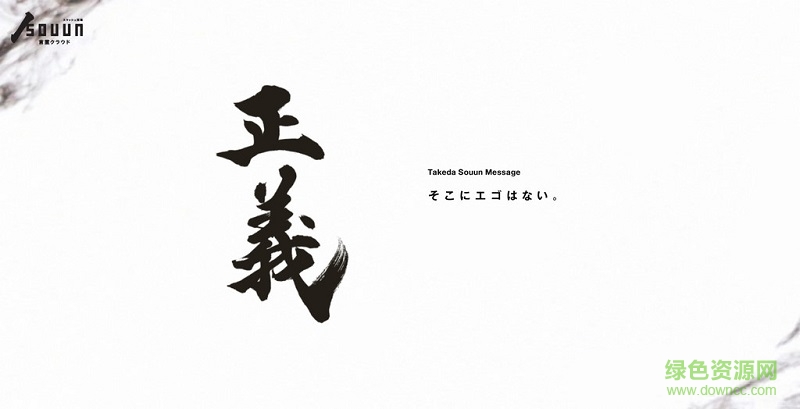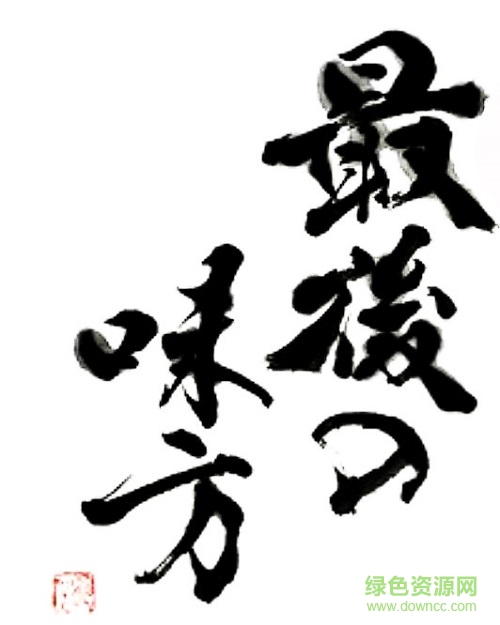
雙云流字體
雙云流字體是日本青年武田雙云自創(chuàng)的書法字體,采用毛筆書法繪就,文字飄逸灑脫,有著漢字書法的獨特美感,深受網(wǎng)友喜歡,快來綠色資源網(wǎng)試試吧!
武田雙云流字體作者介紹
武田雙云,生于1975年,日本熊本縣人,3歲開始跟隨書法家母親武田葉學(xué)習(xí)書法。東京理工大學(xué)畢業(yè)。他現(xiàn)在除了辦個展和主持湘南書道教室,也和音樂家共同舉辦大型書法表演。
雙云流字體
武田雙云流字體點評
在少有的中文網(wǎng)頁介紹里,稱他的書法為“流字體”。不過,似乎網(wǎng)友并不認(rèn)可:“流字體”?跟漢字的寫法差不多嘛,不過字還有點意思!